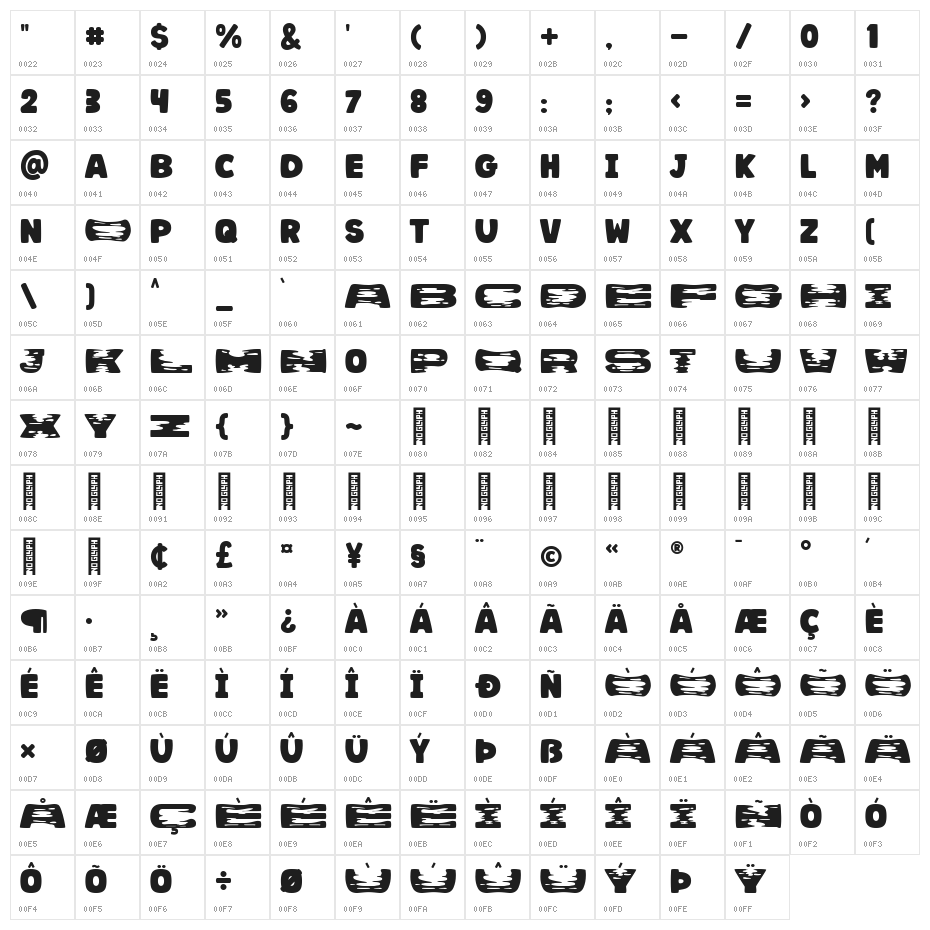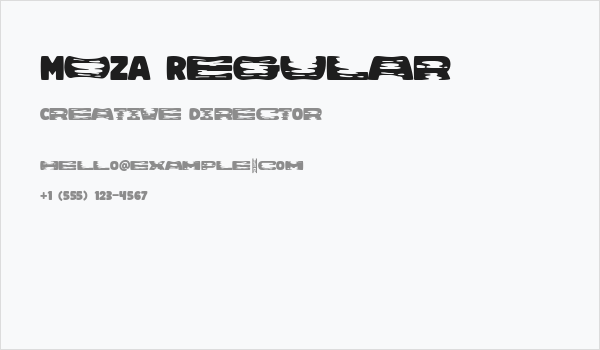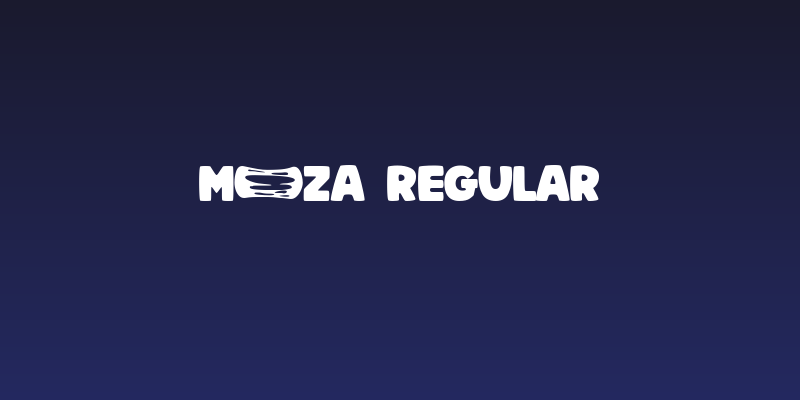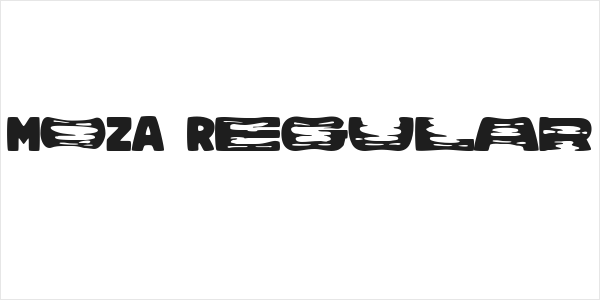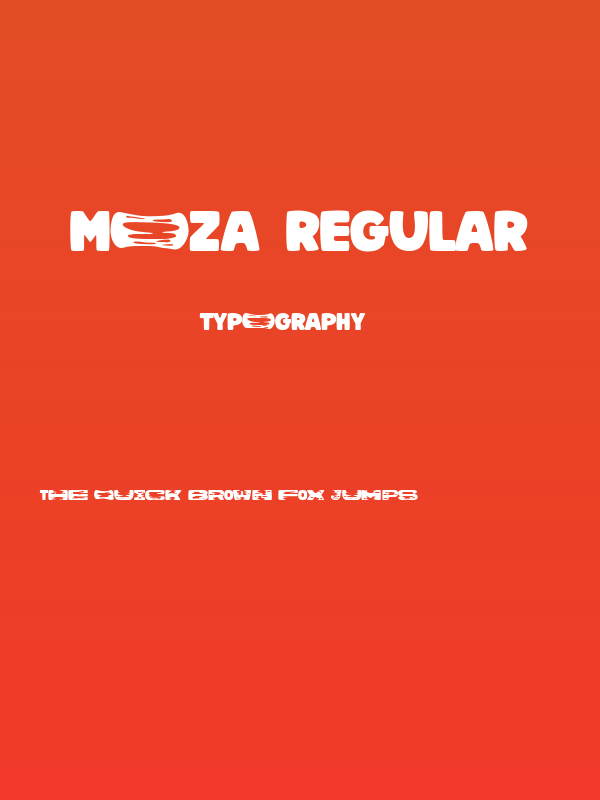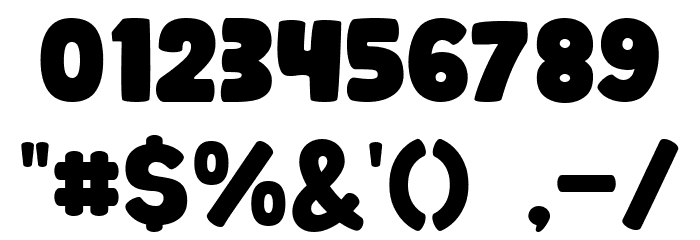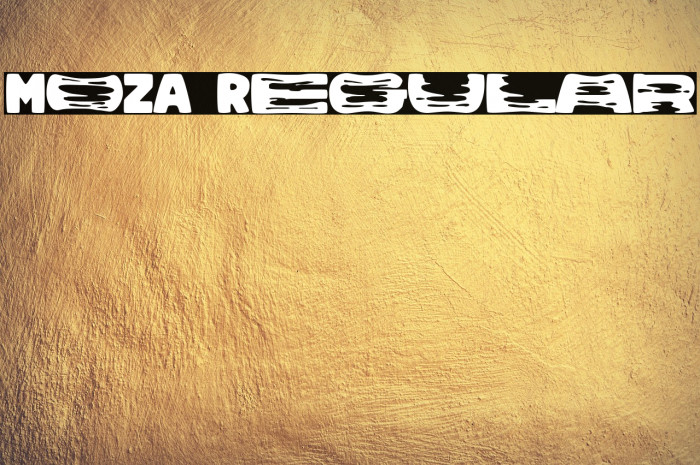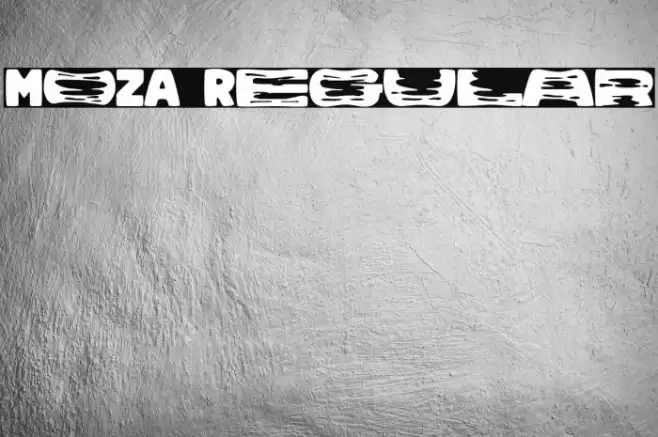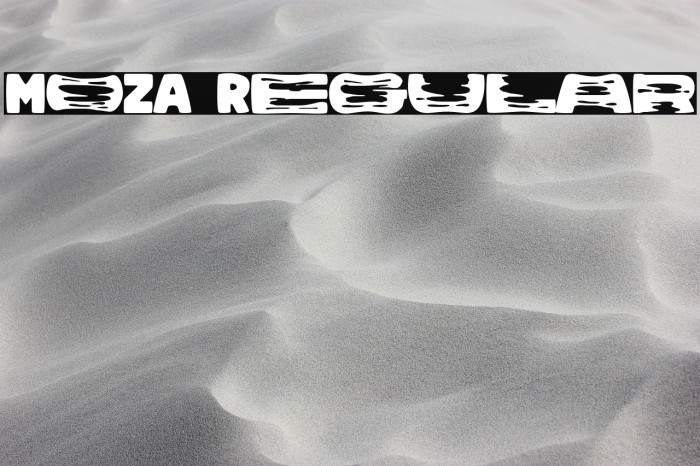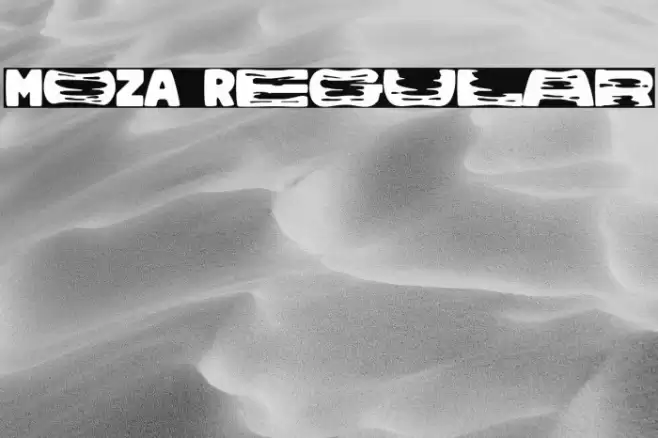
MOZA Regular Font
✎ Distorted Eroded
| Gesamtstil | Vintage |
| Vorgeschlagene Projekte | Ideal for posters, album covers, branding, and any design needing a bold, vintage aesthetic. |